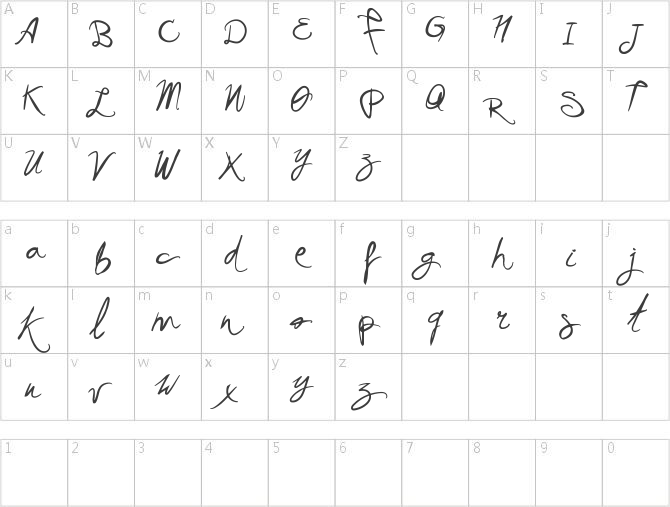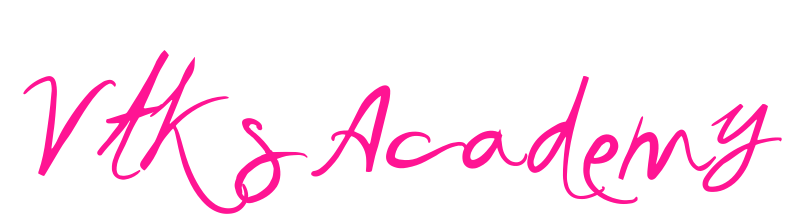
Vtks Academy 詳情頁
字體名稱: Vtks Ac
Vtks Academy
Vtks Academy介紹
Vtks Academy字體字庫是一款讓人賞心悅目、百看不厭的英文字體,適合各類廣告和產品包裝設計應用,字體大小0.03MB,格式為ttf字體,上傳用戶是哼哼哈兮,作者/版權方為未知